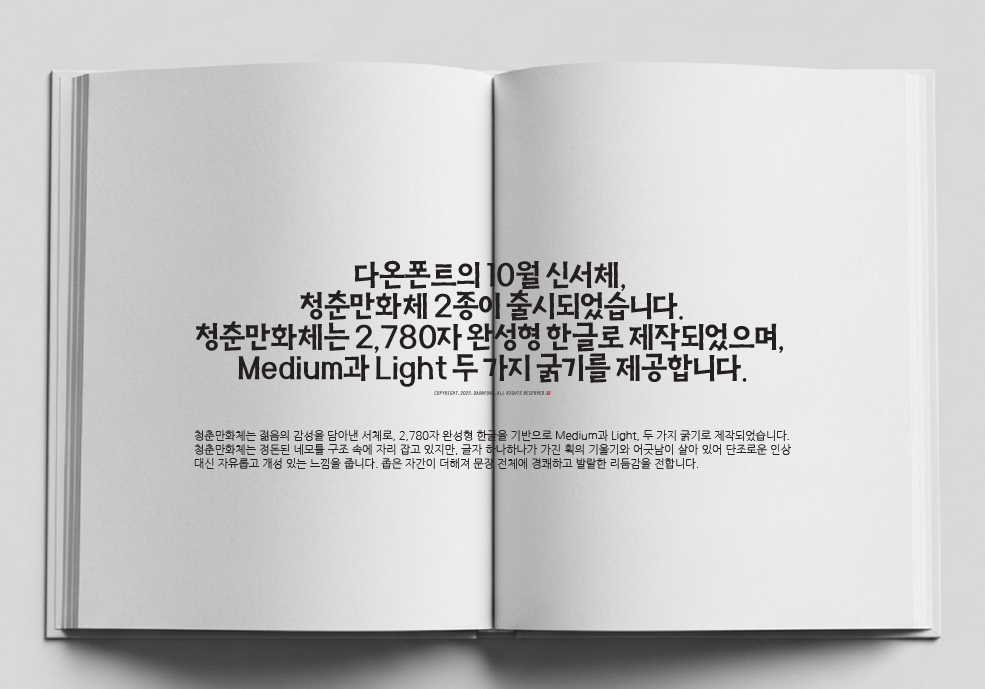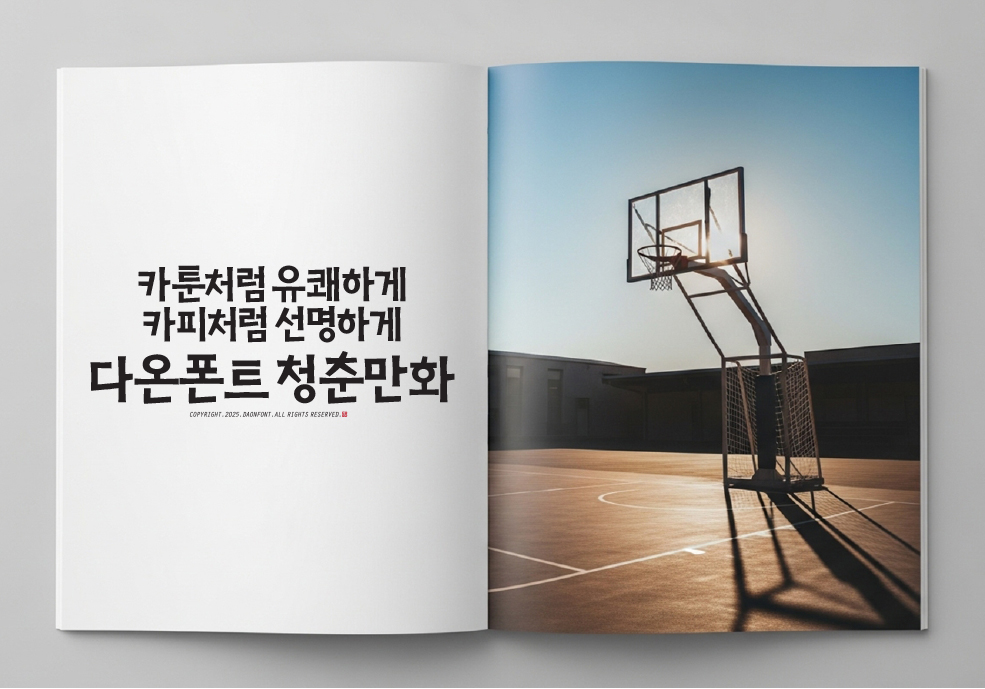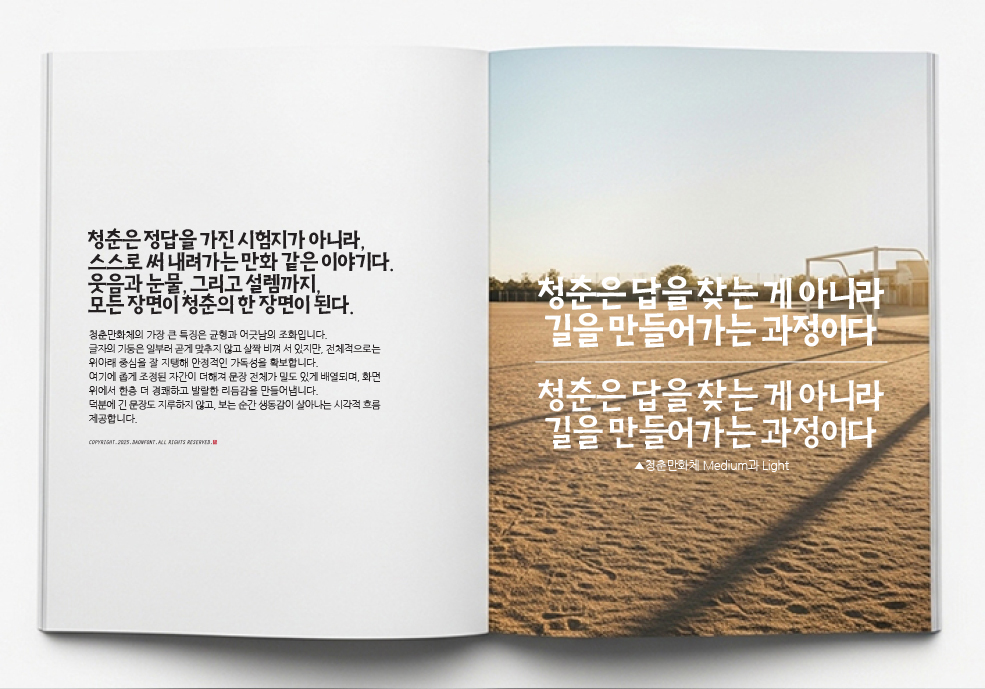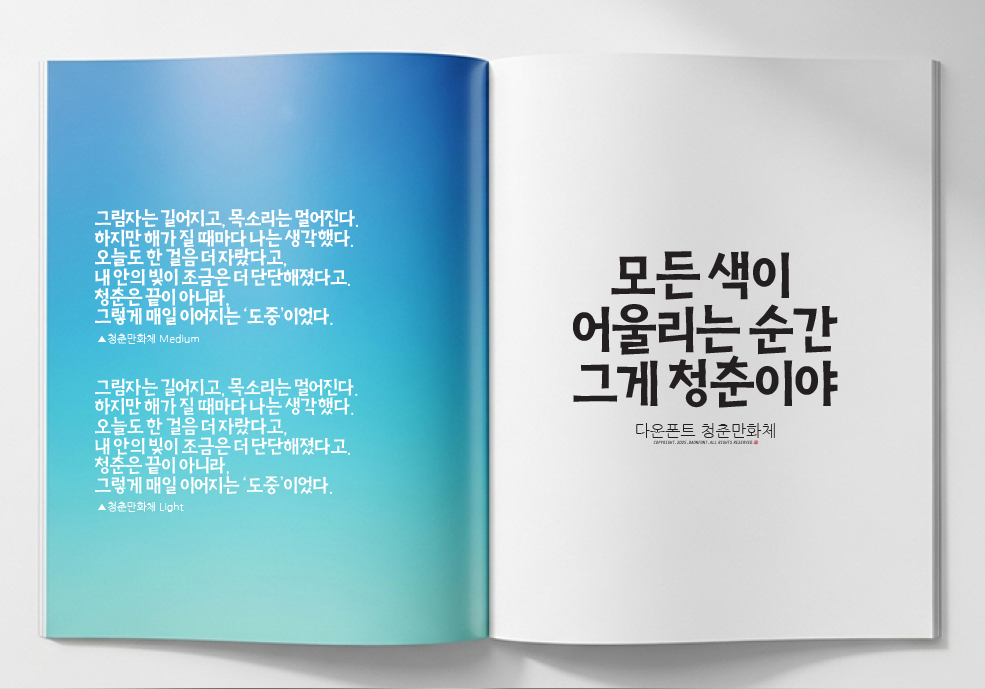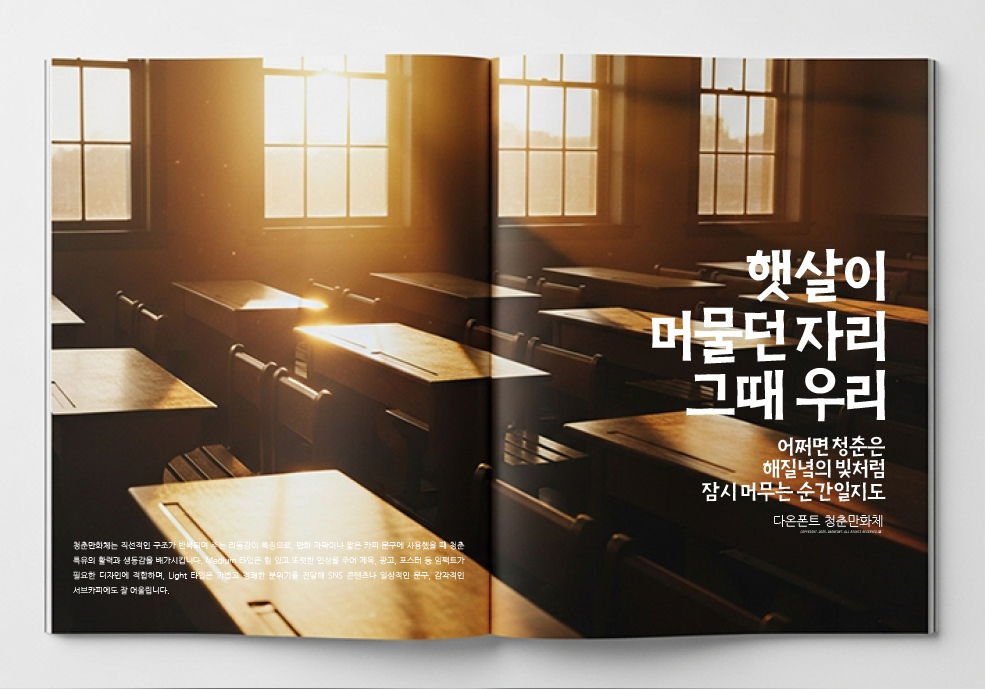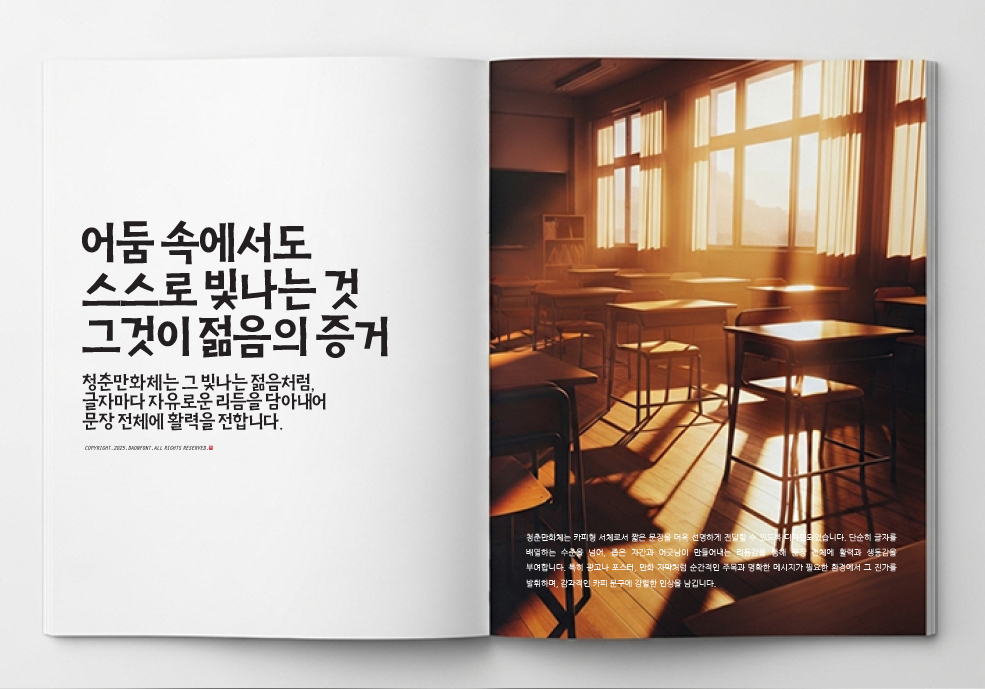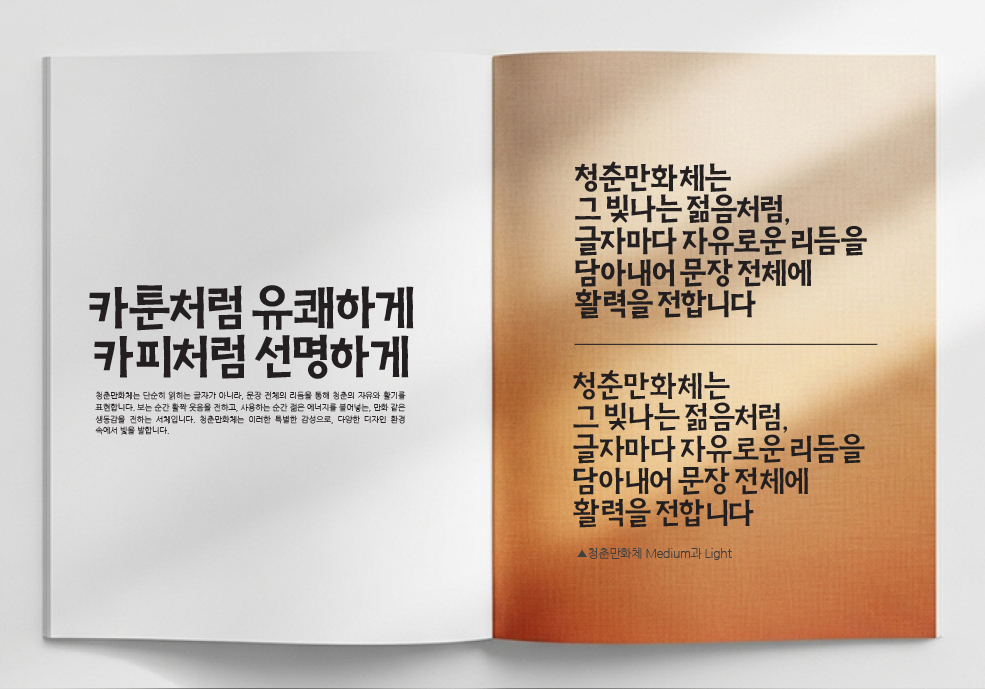
10월 신서체 "청춘만화" 2종 출시 안내
다온폰트의 새로운 서체,
청춘만화체 2종(Medium · Light)이 출시되었습니다.
청춘만화체는 2,780자 완성형 한글로 제작되었으며,
정돈된 네모틀 구조 속에서 글자마다 개성과 자유로움이 살아 있어
단조롭지 않고 감각적인 인상을 줍니다.
또한 좁은 자간이 더해져 문장 전체가 밀도 있게 배열되며,
청춘 특유의 경쾌한 리듬과 발랄한 생동감을 전합니다.
Medium은 제목, 광고, 포스터 등 강렬한 인상이 필요한 곳에 적합하고,
Light는 SNS 콘텐츠나 감각적인 카피에 잘 어울려 다양한 디자인 환경에서 활용도가 높습니다.
청춘만화체는 젊음의 활기와 자유로운 감성을 담은 글씨체로,
여러분의 디자인을 더욱 빛나게 합니다.